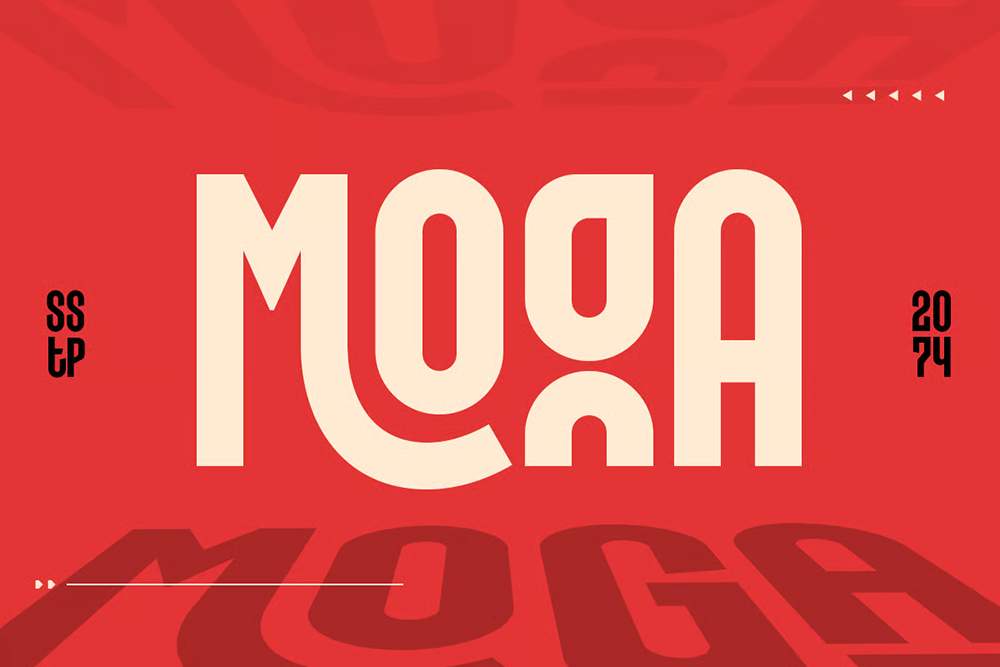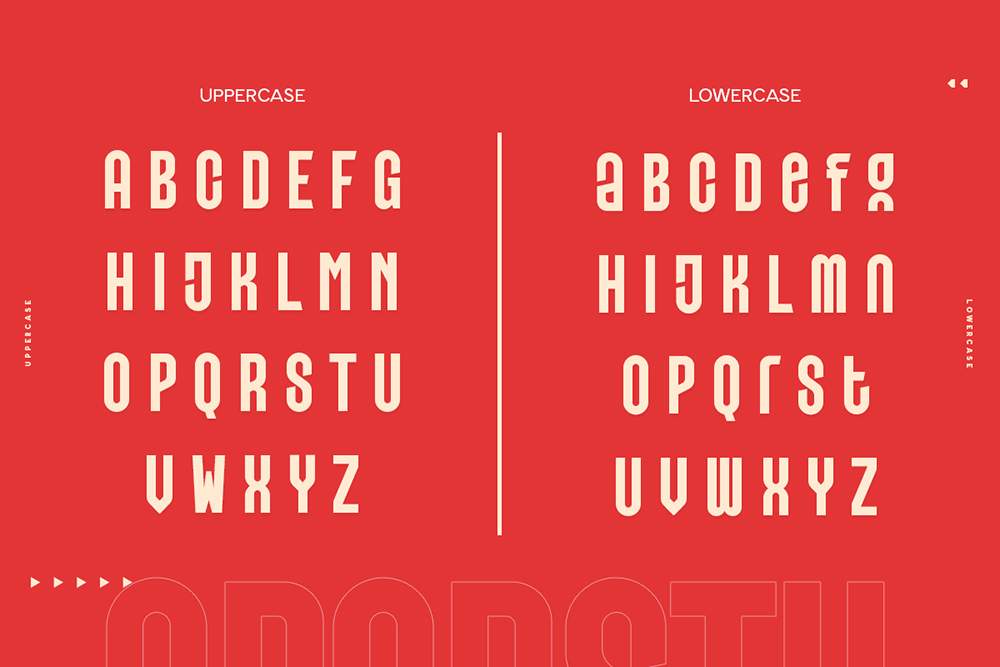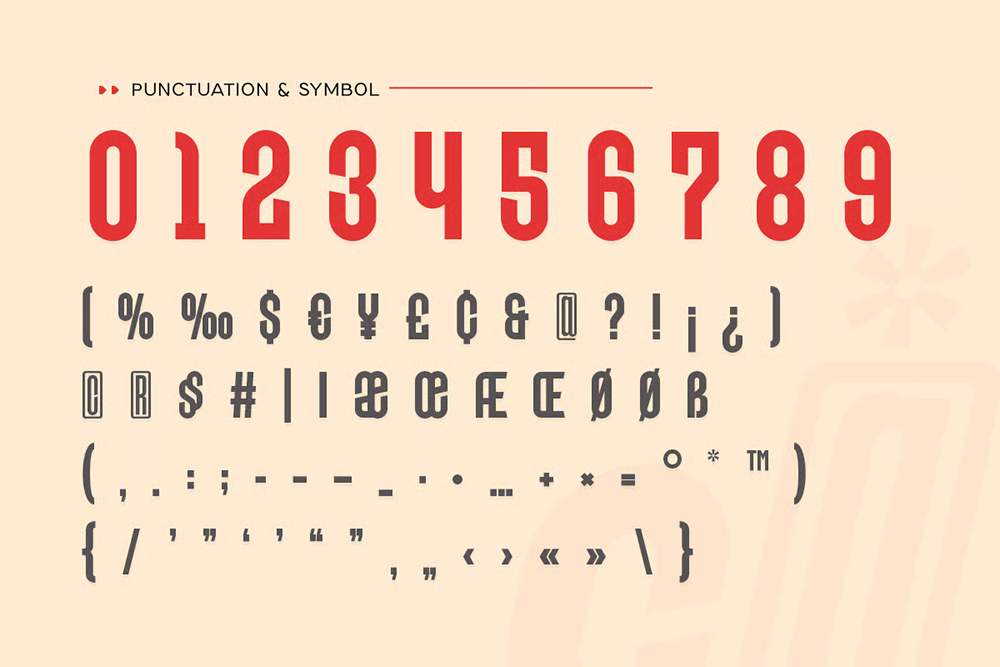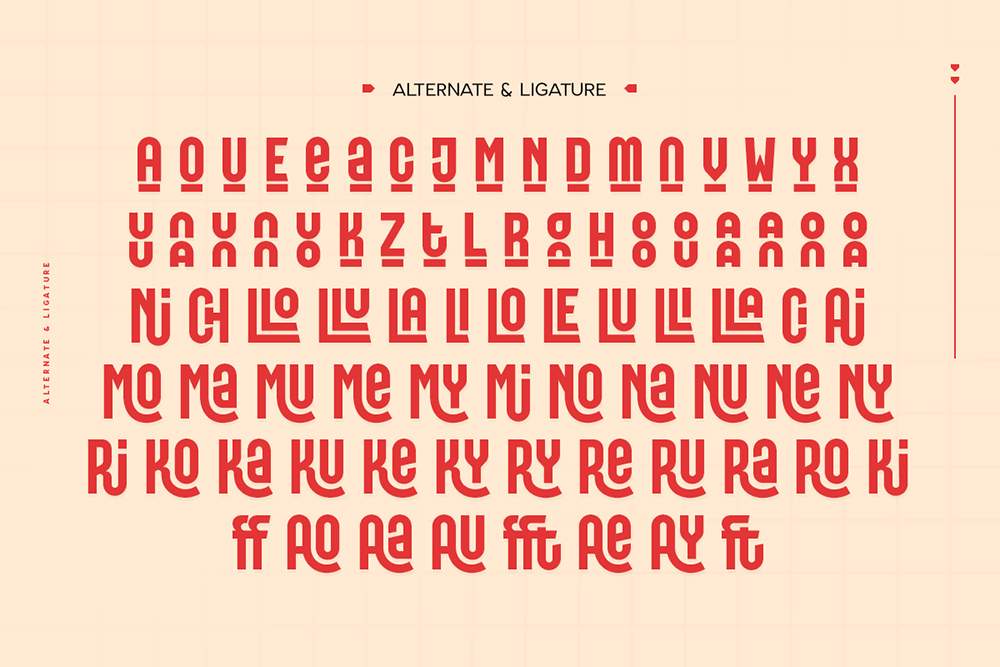
فونت پرمیوم و انگلیسی Moga Font یک فونت بازی فشرده و جسورانه است که برای آوردن انرژی و اکشن به پروژههای خلاقانه شما طراحی شده است.…
فونت پرمیوم و انگلیسی Moga Font یک فونت بازی فشرده و جسورانه است که برای آوردن انرژی و اکشن به پروژههای خلاقانه شما طراحی شده است. فرمهای حروف قوی و فشرده آن، حضوری قوی به آن میبخشد و آن را برای لوگوهای بازی، برندسازی ورزشهای الکترونيکی و طرحهای اکشنمحور ايدهآل میکند. اين فونت برای برتری در طراحیهای رقابتی و سريع ساخته شده است و تضمين میکند که برند يا پيام شما قوی است و تأثيری ماندگار بر جای میگذارد.
مزایای استفاده از فونت لاتین Moga چیست؟